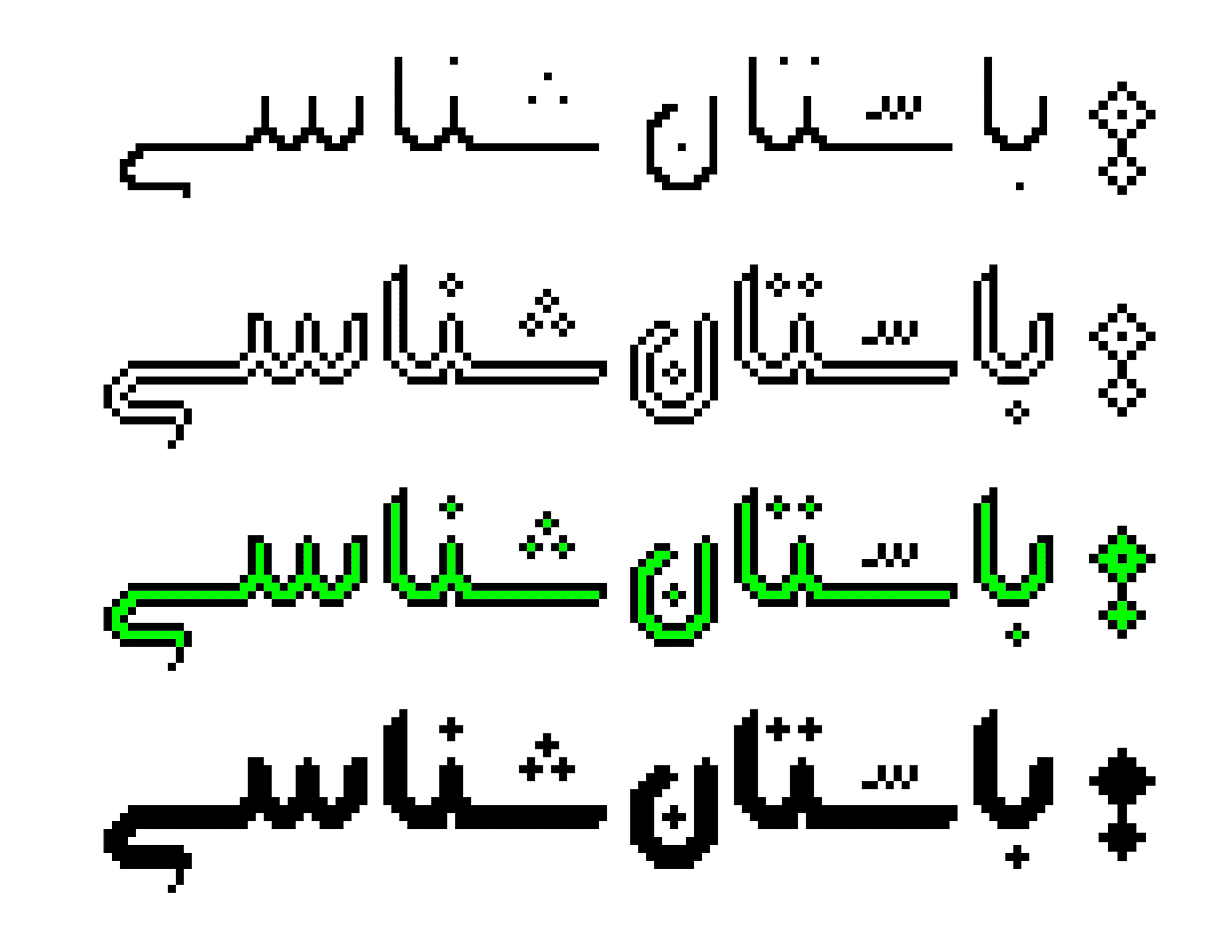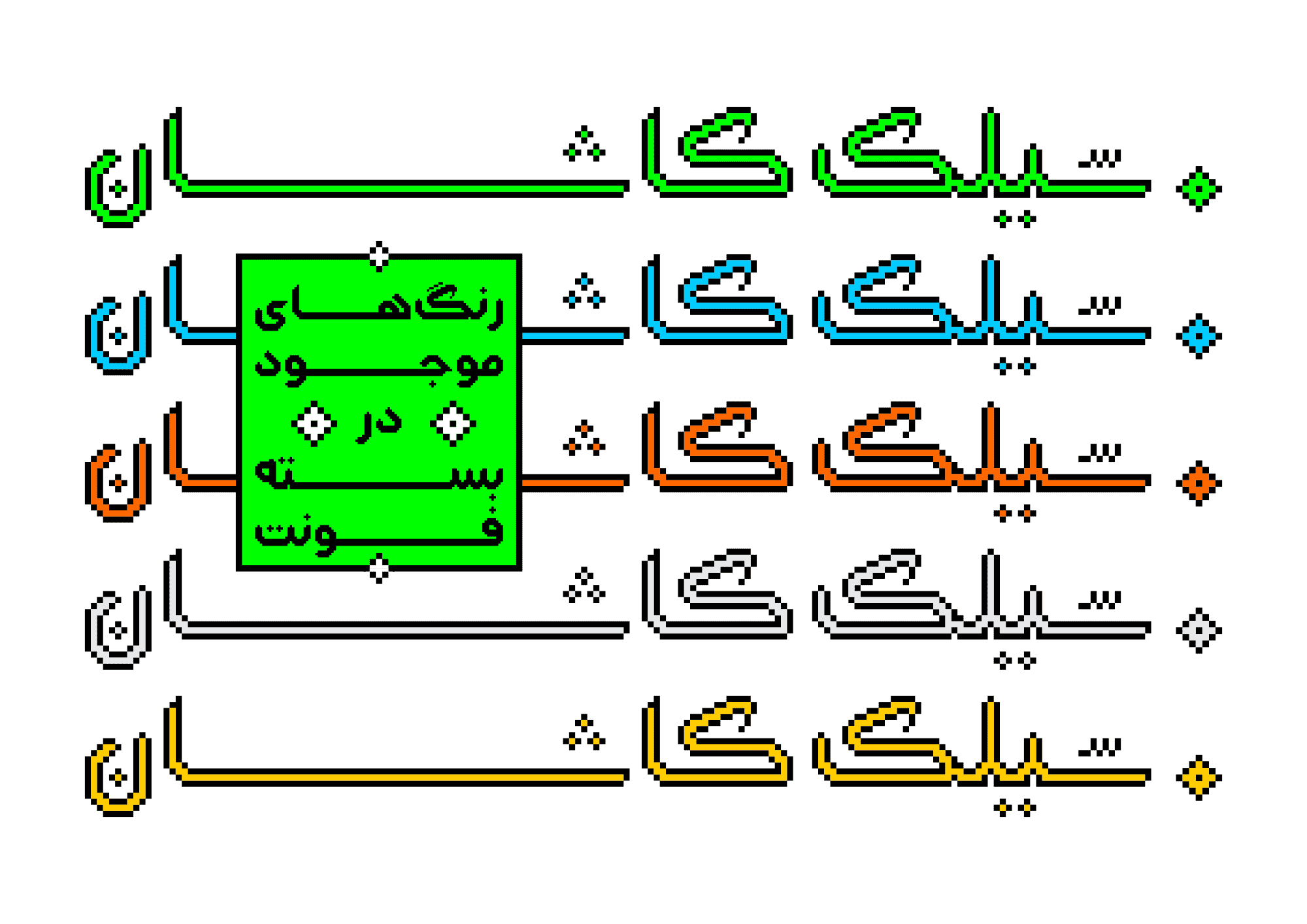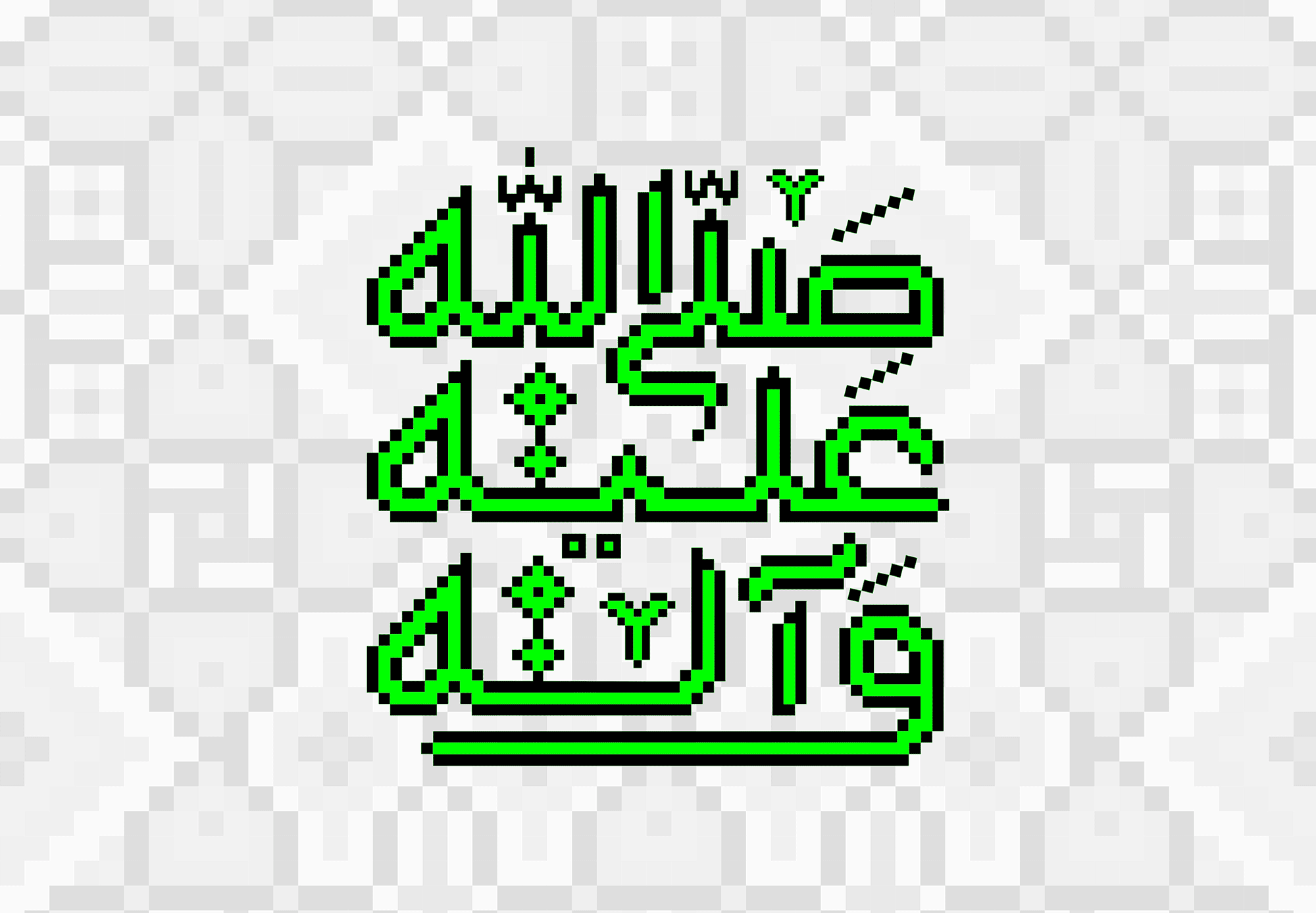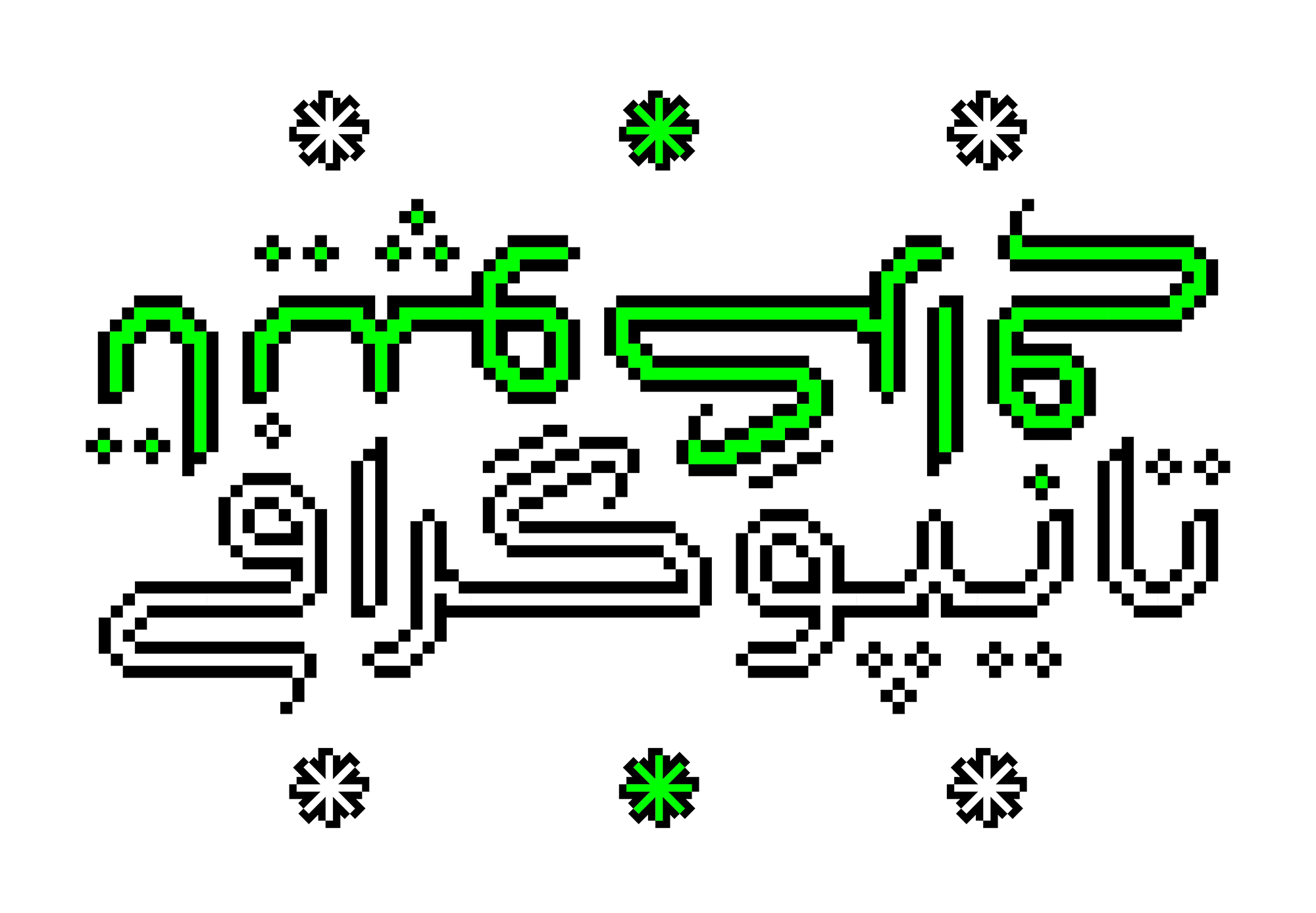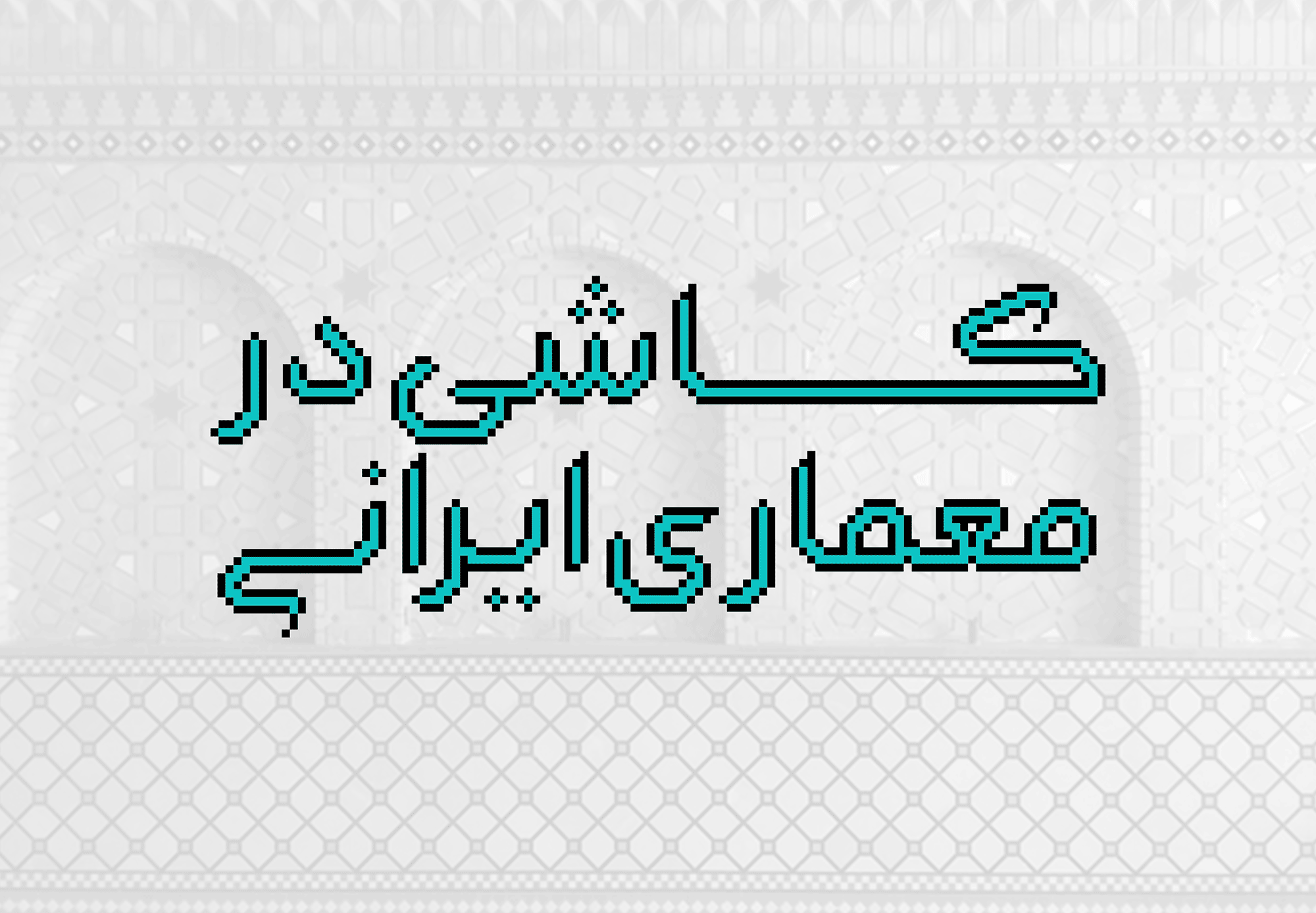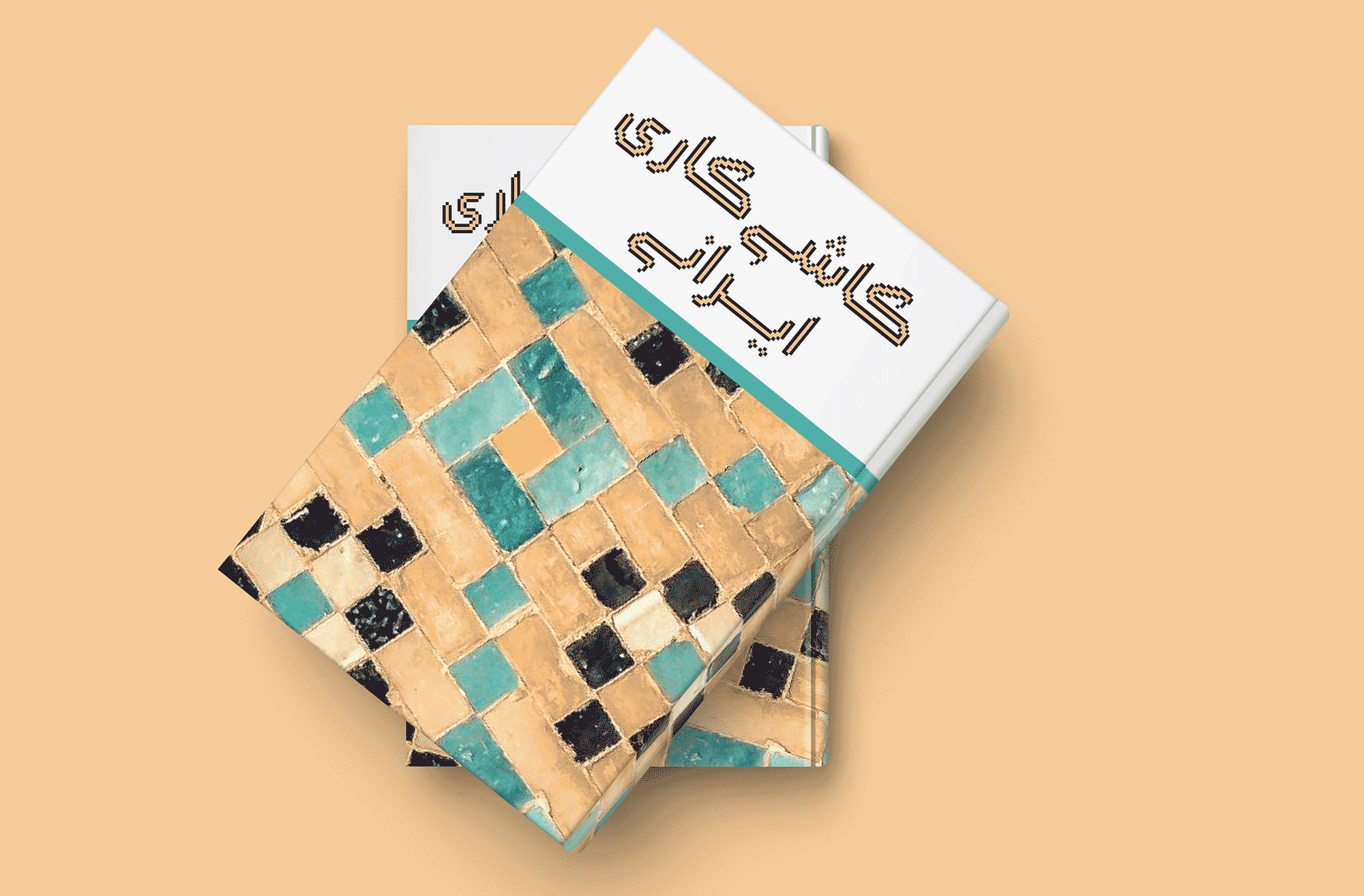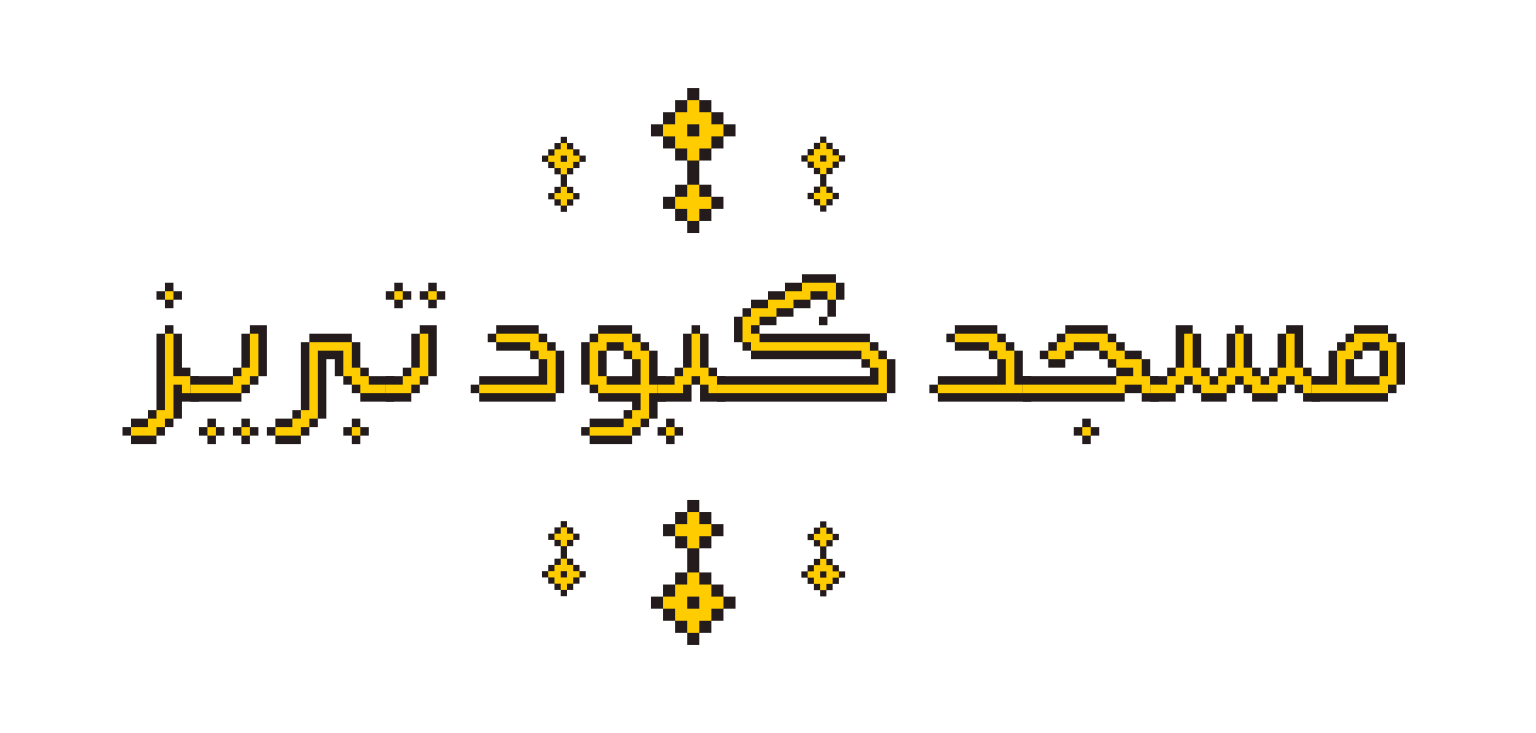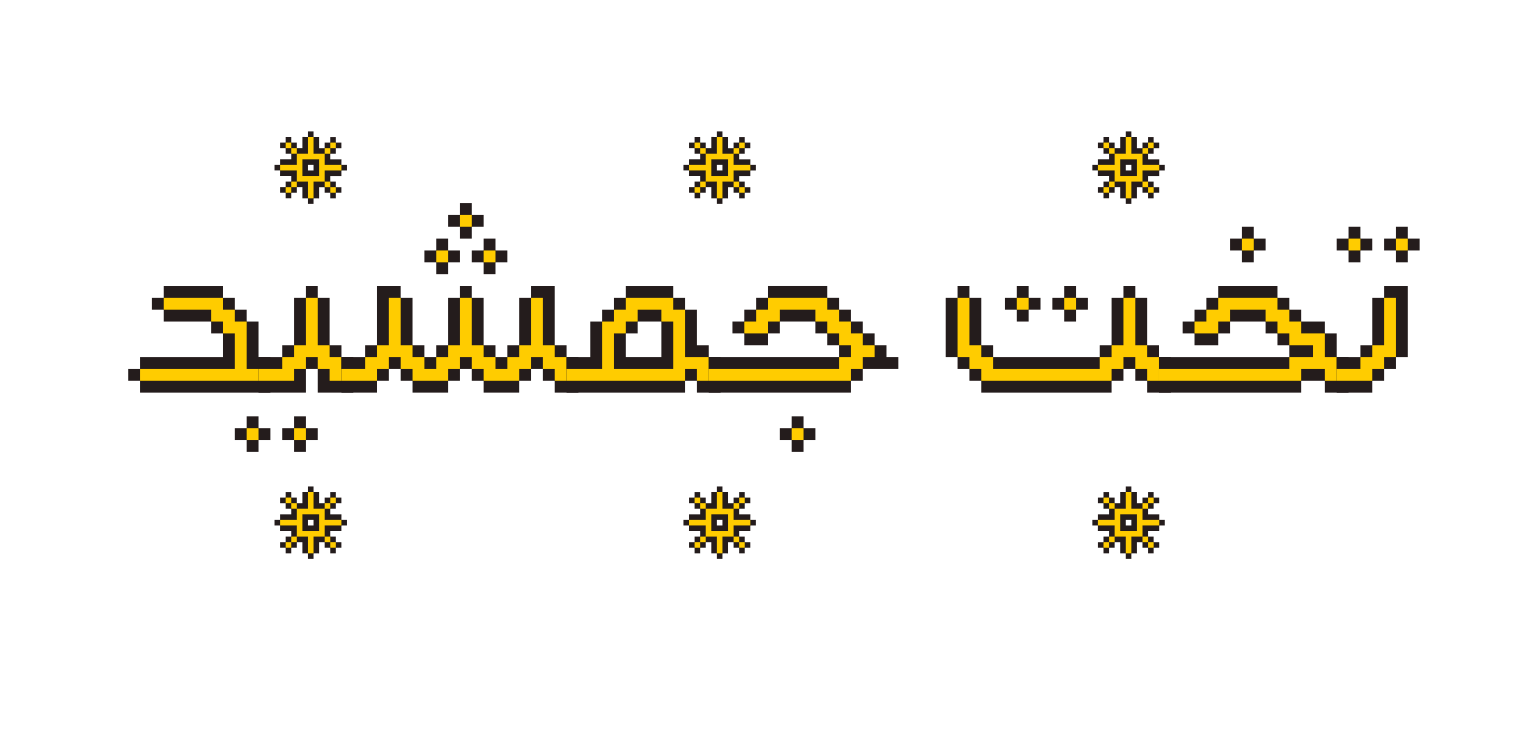
فونت گلچین شکل امروزی شده و کاربری خط ساقه گنبدی است.
خط ساقه گنبدی نوعی برخورد مینیمال با طراحی حروف است. طراحی حروف پیچیده فارسی با منحنیهای زیاد در یک شبکه محدود شطرنجی کاری بسیار مشکل است. وحید یعقوبلو در طراحی تایپفیس گلچین محدودیتهای بیشتری نیز برای رعایت سیستم حروفچینی در فونت داشته است. حل این مشکلات منتج به طراحی فونت گلچین شده است که در ادامه میتوانید ببینید و فونت آن را خریداری کنید.
فونت رنگی گلچین در پنج رنگ